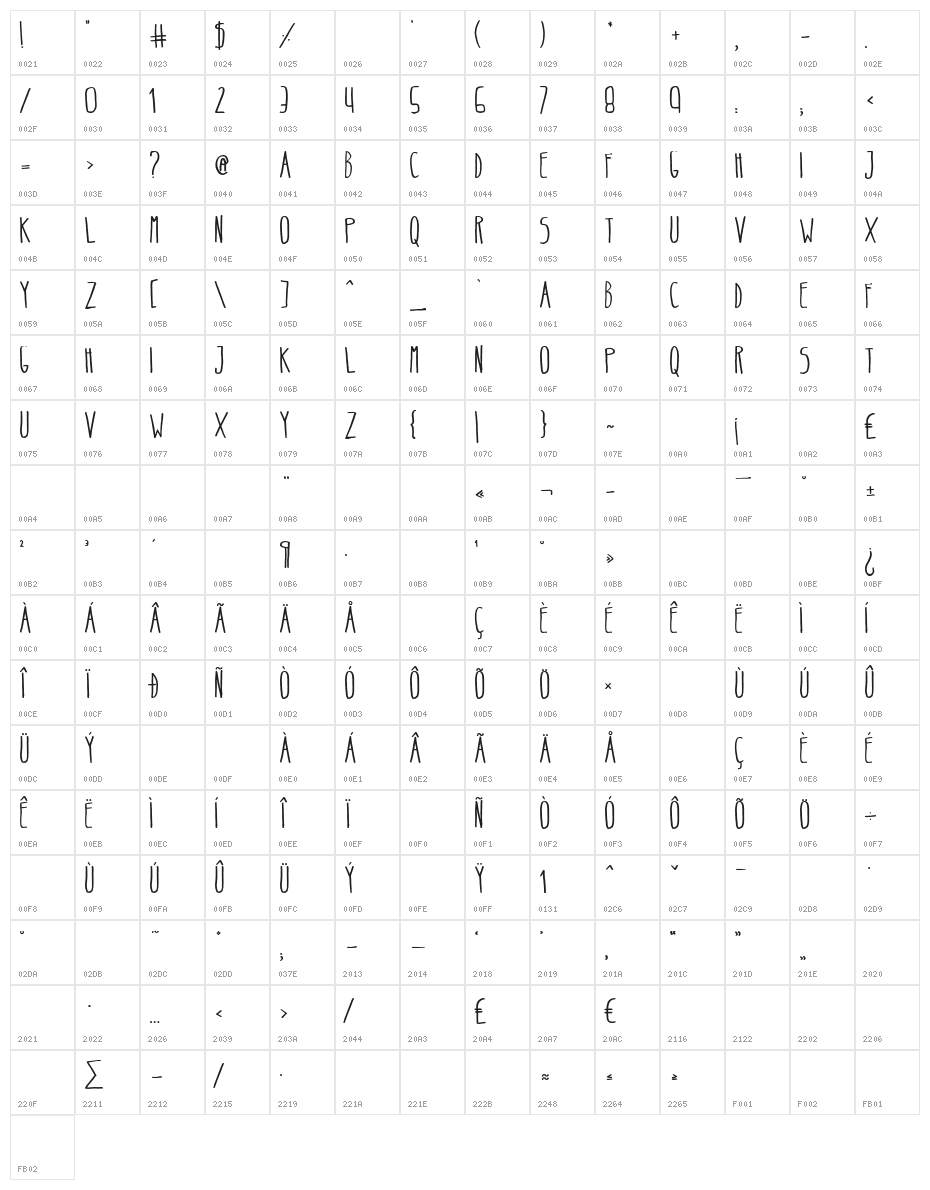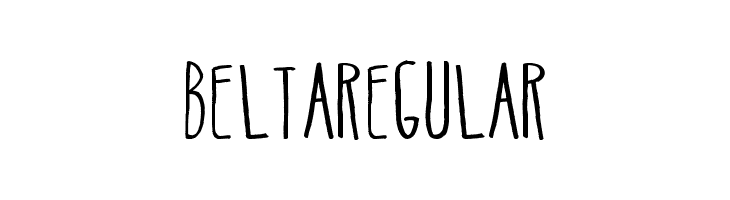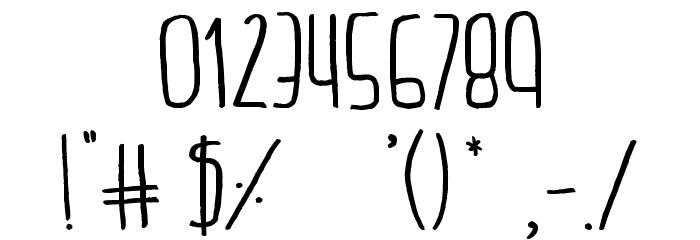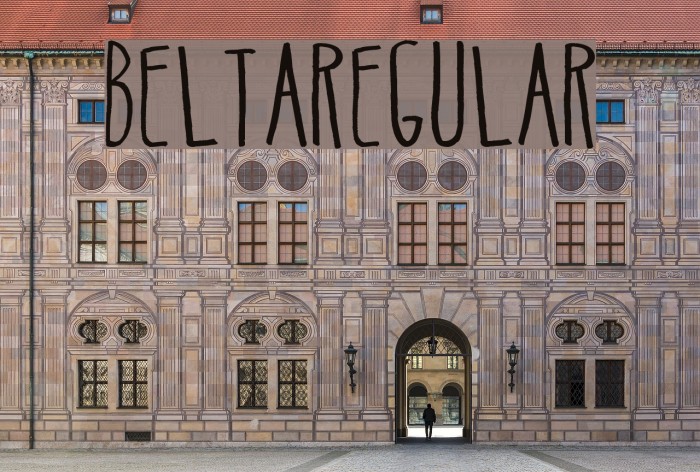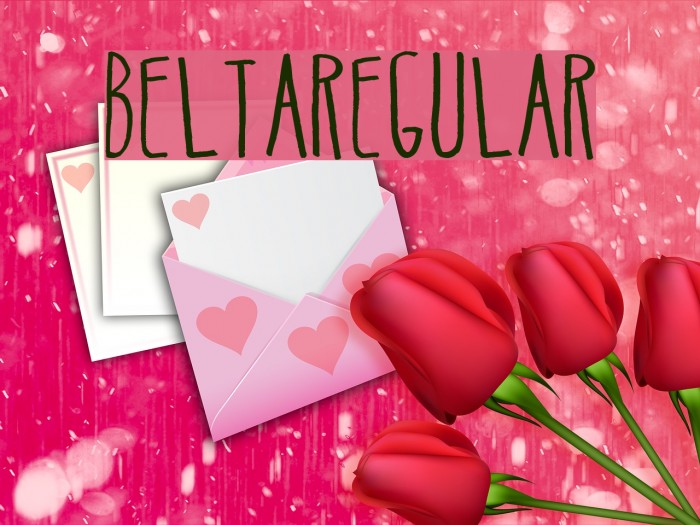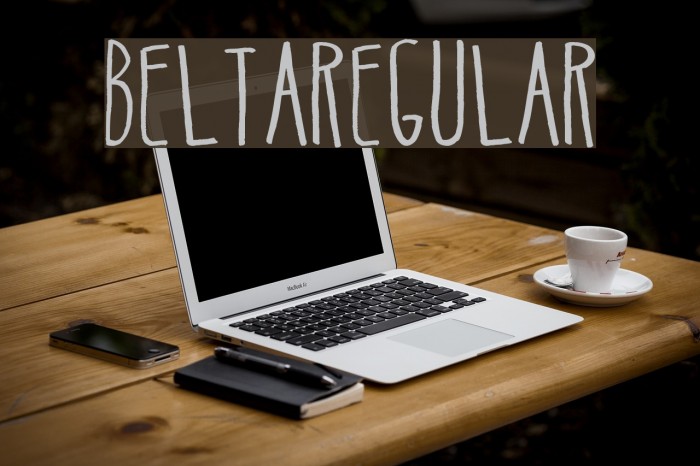
BeltaRegular Font
Fonts by exe.vis.ne.jp
| Proiecte propuse | Ideal for children's books, greeting cards, posters, and branding projects that seek a friendly and approachable vibe. |